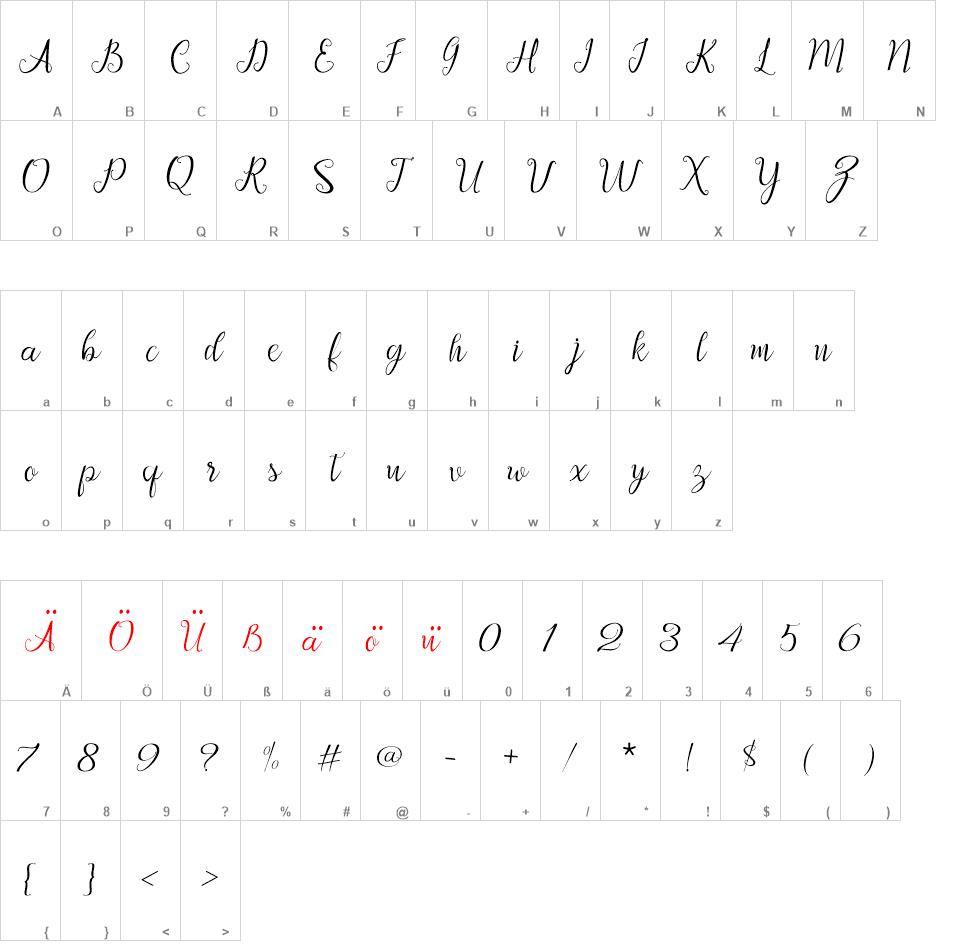
Afrile
Afrile  font
Afrile
Afrile Script ein neues, frisches & modernes Script mit handgefertigtem Kalligraphie-Stil, dekorativen Charakteren und einer tanzenden Grundlinie! So schön auf Einladung wie Grußkarten, Branding-Materialien, Visitenkarten, Zitate, Plakate und vieles mehr !!